书法,是中国及深受中国文化影响过的周边国家和地区特有的一种文字美的艺术表现形式。包括汉字书法、蒙古文书法、阿拉伯书法和英文书法等。其"中国书法",是中国汉字特有的一种传统艺术。
从广义讲,书法是指文字符号的书写法则。换言之,书法是指按照文字特点及其含义,以其书体笔法、结构和章法书写,使之成为富有美感的艺术作品。汉字书法为汉族独创的表现艺术,被誉为:无言的诗,无行的舞;无图的画,无声的乐等。
本期推荐13款免费商用书法体。
2016年,庞门正道联合了13位设计师,一起开发了一款商用免费字体,《庞门正道标题体》,下载量也接近1万。最近庞门正道又推出一款全新的免费字库:庞门正道粗书体,字体书写作者来自90后的:车港敏。
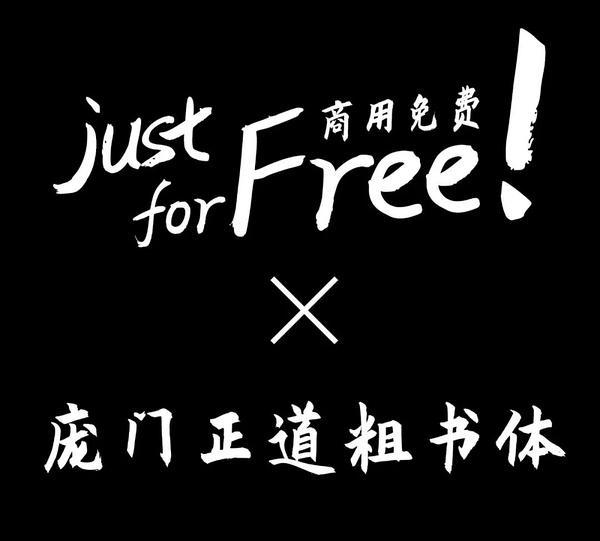
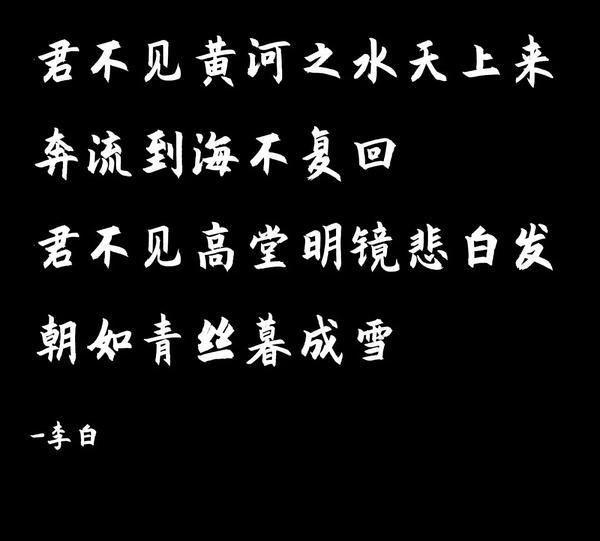
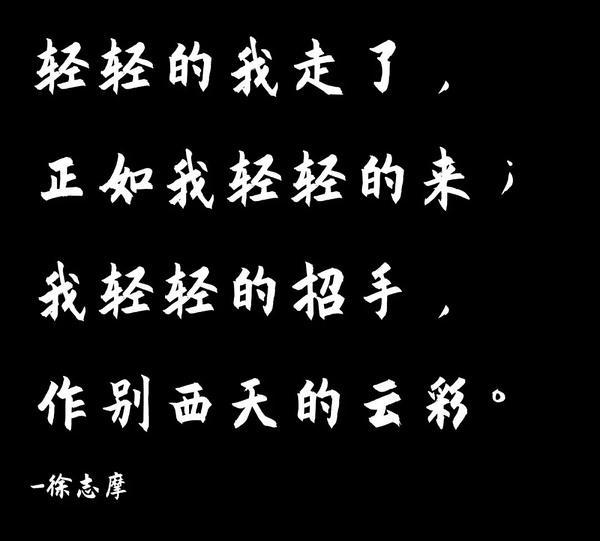
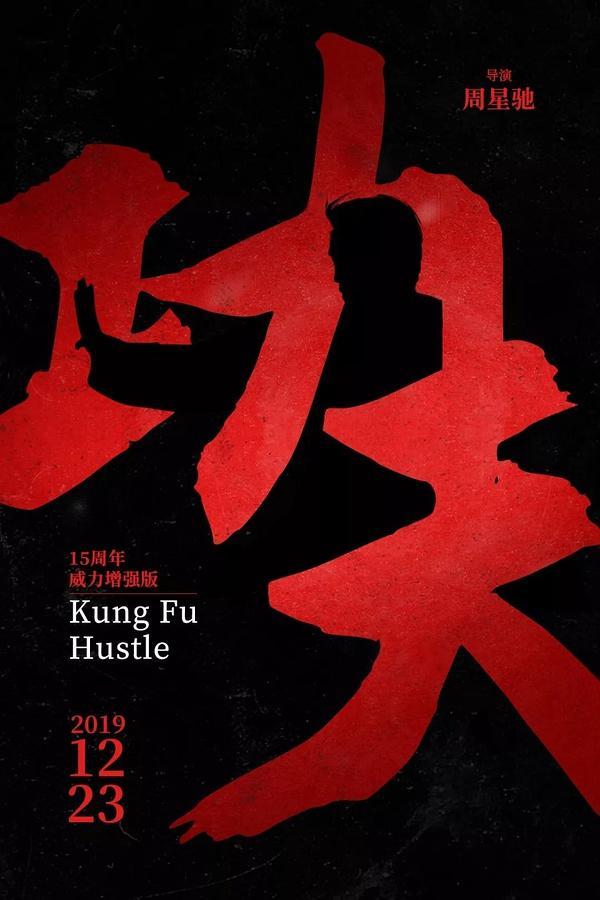
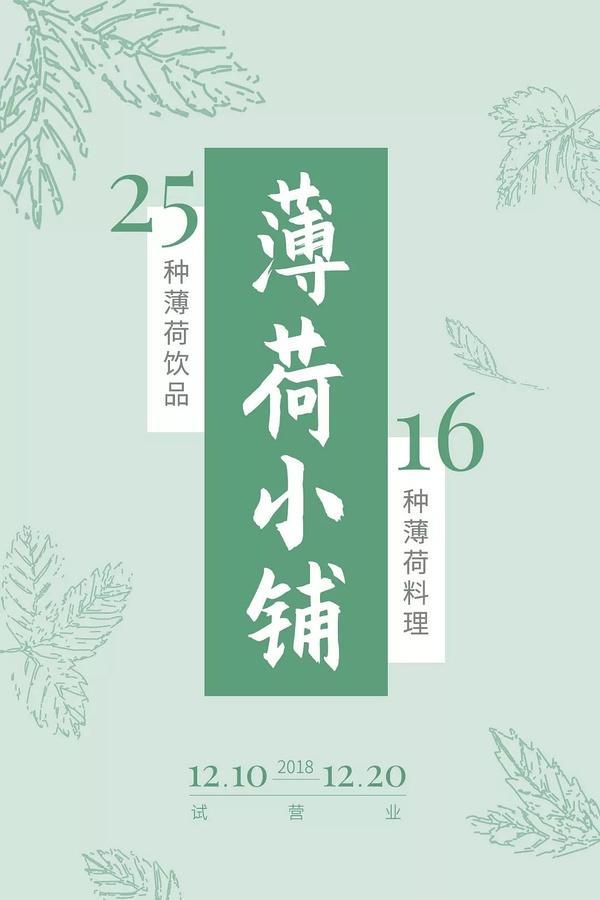
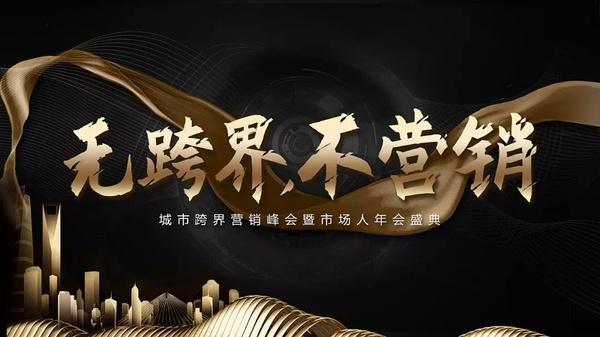
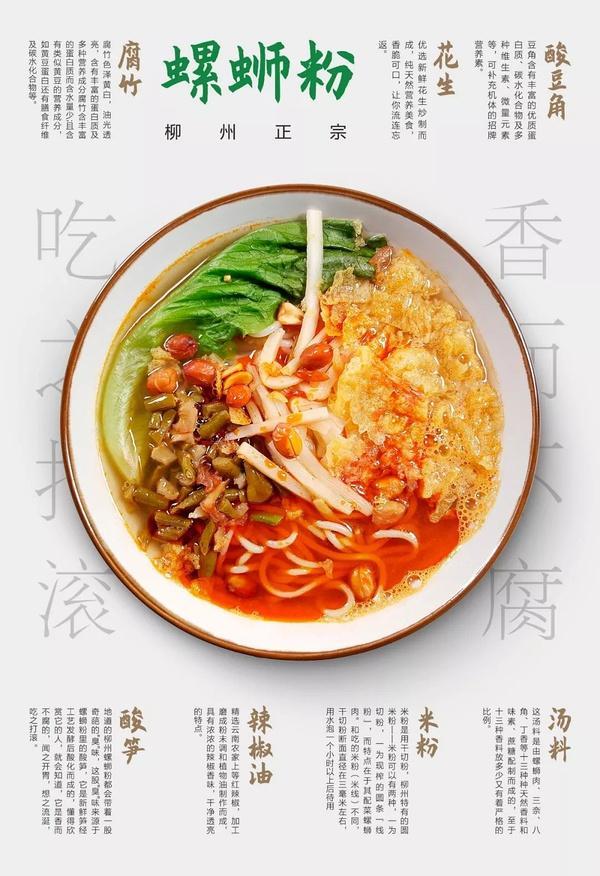
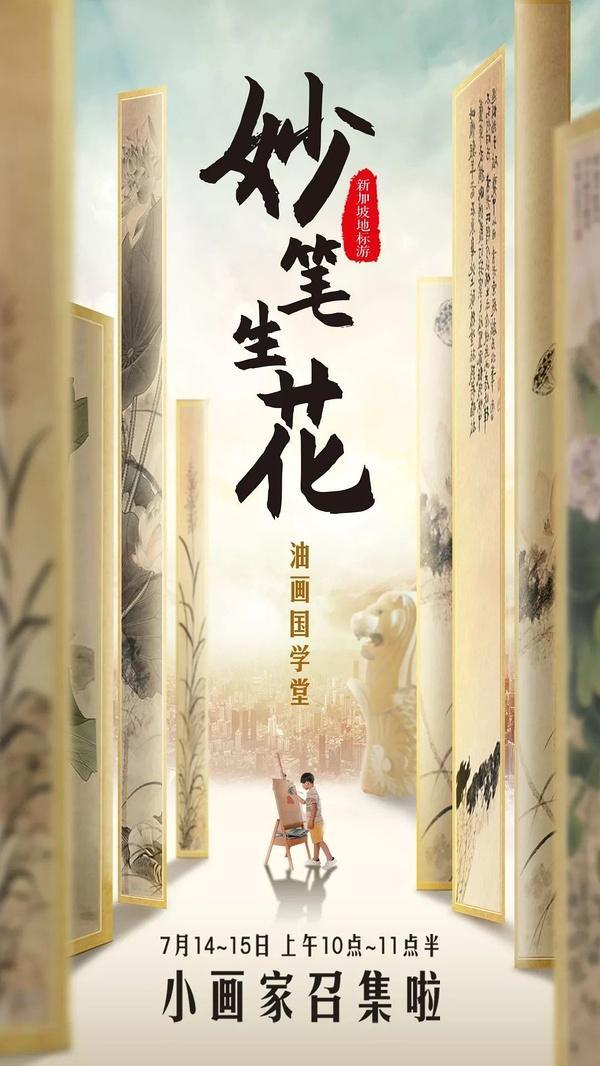
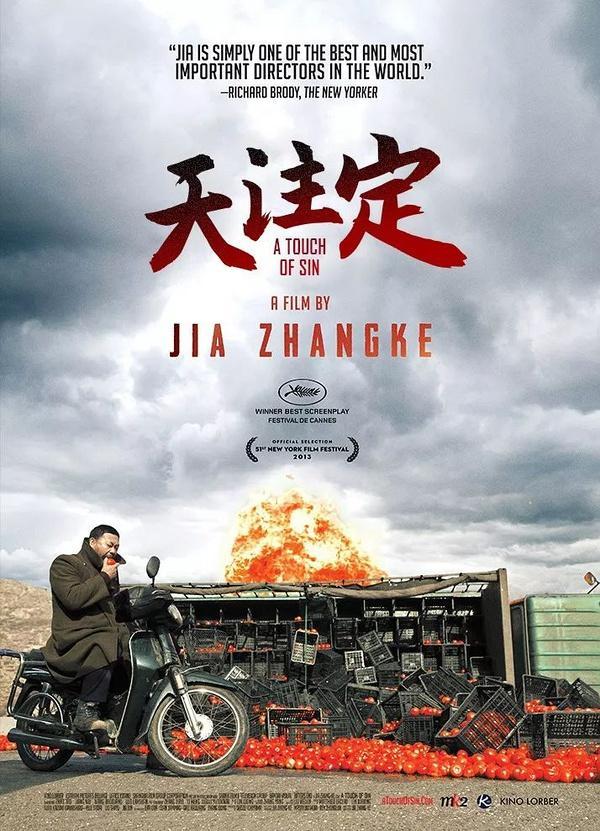
庞门正道真贵楷体
庞门正道真贵楷体是庞门正道发布的又一款免费可商用楷书书法字体。
真贵楷体这个字体是由庞门正道阿门的父亲庞真贵,于2018年初开始写起,历时两年而成,是一款既有性格,又非常易用的书法楷体,现在,庞门正道真贵楷体字体终于面世了,阿门也将其开放,给予大家永久免费商用!
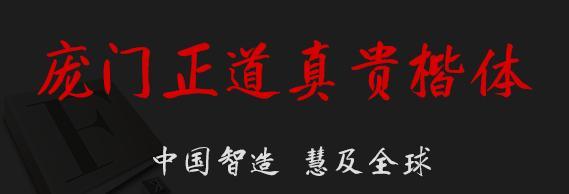
庞门正道真贵楷体,从庞真贵74岁开始写,写过了75岁,再到76岁时,字库制作完成并发布,经历了三个春秋,终于等来了这款字的诞生!
江西拙楷体
江西拙楷升级版是一款可免费商用的古风字体,这套字体是一套手写字体
可以用于一些古风作品的设计,每个字的笔画是没有统一标准的,所以看上去显得不够规范,但是会有一种手写的自然之感。
“江西拙楷”是一套手写楷体,笔画会带有一些书写的痕迹,每个字的笔画是没有统一标准,所以会有一种手写的自然之感。
这款字的性格和江西很像,低调内敛,朴实无华毫不张扬,就命名为江西拙楷,希望通过这套字体让江西增加点曝光度,让更多人来了解江西。
鸿雷板书
鸿雷板书简体,字体是手写风格,这类免费字体并不多见呢。何谓板书简体呢?因为他是由字体制作者鸿雷使用手绘板写的字体。
作者是一个字体爱好者,在抄写简体版千字文时想到制作一套字体,经历一个多月的时间手写完成,最后制作成鸿雷板书简体,现在公开免费个人及商用
演示悠然小楷
演示悠然小楷字体,如青竹新生,露拙朴之气,是一款清新毛笔体,笔画分明,结构清晰,没有过度的连笔和飞白,对阅读识别更为友好!
《辞海》有语:形体方正,笔画平直,可作楷模。说的,便是楷书 楷体中以小楷清秀流丽、润泽含蓄,可填补系列字的中庸之位,于是便有了这款演示悠然小楷。
初看演示悠然小楷,可能并不觉得惊艳,再品,却会发现透着质朴、率真的气息。正如尚在象牙塔中的作者本人,那是未经雕琢的拙朴书生气。
接下来,我们一起体会悠然小楷的这股拙气。
悠然小楷的笔画力度分布均衡,起收有序,没有太过强烈的对比,自然沉劲而不漂浮;
在小楷的基础上有些行楷的影子,为字体增添了灵动,但又有克制,形成停而不断、笔断意连之态;
部分笔画细节可能并不完美,不够顺滑,但这份未经雕琢,又何尝不是一种难得的拙朴;
演示春风楷
演示春风楷是一款支持永久免费商用的楷体字体,由Keynote研究所制作推出,字稿作者:徐占海,军人出身,1983年入伍。
每日笔耕不辍练习写字。字体笔触粗实,书写端正大气,适合应用于艺术设计、平面宣传设计、网页设计,书法字帖等领域
演示夏行楷
演示夏行楷是一款由Keynote研究所发布的免费商用楷体,这次一共发布三款楷体,取以四季中的三季,夜热依然午热同 开门小立月明中,相信有不少喜欢这款字体的朋友!
字稿作者:刘锡栋
中国漓江书画艺术家协会理事丨北京中国书画研究院研究员丨中国民族硬笔书法家协会会员丨中国楹联学会会员丨黑龙江楹联家协会会员丨高级政工师,已退休
字体制作:人生哥(和他的半自动电脑)
演示秋鸿楷
演示秋鸿楷是一款支持全媒体永久免费商用的书法艺术字体,由Keynote研究所制作推出,字稿作者:叶运鹏,高中教师丨辽宁人丨98年加入农民书画家协会。
字体笔触粗实,书写端正大气,适合应用于艺术设计、平面宣传设计、网页设计,书法字帖等领域,欢迎喜欢演示秋鸿楷的朋友前来下载使用。
演示佛系体
演示佛系体是有80岁的纪国才老先生亲手写的独具风格佛系字体,演示佛系体许多写法与小篆类似,诸多奇特的偏旁部首写法,是现代简体繁体都不具备的。
演示佛系体是一款风格十分特别的字体,纪国才老先生一生酷爱书法,在80岁这年亲手写了一套独具风格的字体,这套字体看似随意,但是蕴含着老先生一生的阅历和经验,随意之中又带点不随意。
字体整体乍看之下,似以繁体字为主。但多看一些,才发现,诸多奇特的偏旁部首写法,是现代简体繁体都不具备的。
仓耳周珂正大榜书
仓耳周珂正大榜书字体是仓耳字库推出的一款适应于任何用户全领域永久免费商用的书法艺术字体,字体笔触粗细适中,字形端正,具有很好的视觉感,适合应用于艺术设计、平面宣传设计、网页设计,书法字帖等领域
笔画丰满圆润,在收笔处将笔锋适可而止地连续,构成滑润的圆弧形,使得字体视觉上丰满有力。
其他,字体的钩笔画极点尖利,与圆润的收笔构成比照,使得笔画有干净利落之感。
该字体的全体笔画十分紧凑,许多笔画都粘连在一起,使得字体全体紧凑丰满,粗大健旺有力。
方正楷体
方正楷体源于上海印刷技术研究所“华文楷体”字稿。原“华文楷体”诞生于20世纪40年代,新中国成立后一直是主要使用的铅字楷体。在此期间,上海字模一厂、上海印刷技术研究所等单位进行了数次改良,并添加了简体字。
方正楷体的结构秀丽匀称,笔画圆润柔和,横竖笔画的粗细变化不大。这款字体被大量应用于报纸、杂志和书籍中的正文,在教科书中最为常见。
钟齐志莽行书
钟齐志莽行书字体是由上海钟齐字库公司根据书法家韦志莽先生毛笔书法字库开发而成的一款中文行书书法字体。书法家韦志莽拥有自主版权,禁止未经授权的商业运用。钟齐志莽行书字体广泛适用于广告设计、包装设计等方面。
韦志莽,男,号东邪。广西柳江县人,生于1971年,一九九二年毕业于广西艺术学院。自幼酷爱绘画,垂髫之年即仰慕徐悲鸿先生画风,并立志有所作为。
多年潜心研究艺事,不趋时风,不求时名。擅长油画、国画、书法。
国画上最钟情于吴昌硕大师,书法则恪守王赵正脉。
钟齐流江毛草
钟齐流江毛草体是由钟齐字库公司根据书法家流江先生的草书书法开发而成的一款草书书法字体,字形潇洒飘逸,可用于印刷包装、平面设计、广告创意、毛笔书法等行业领域。